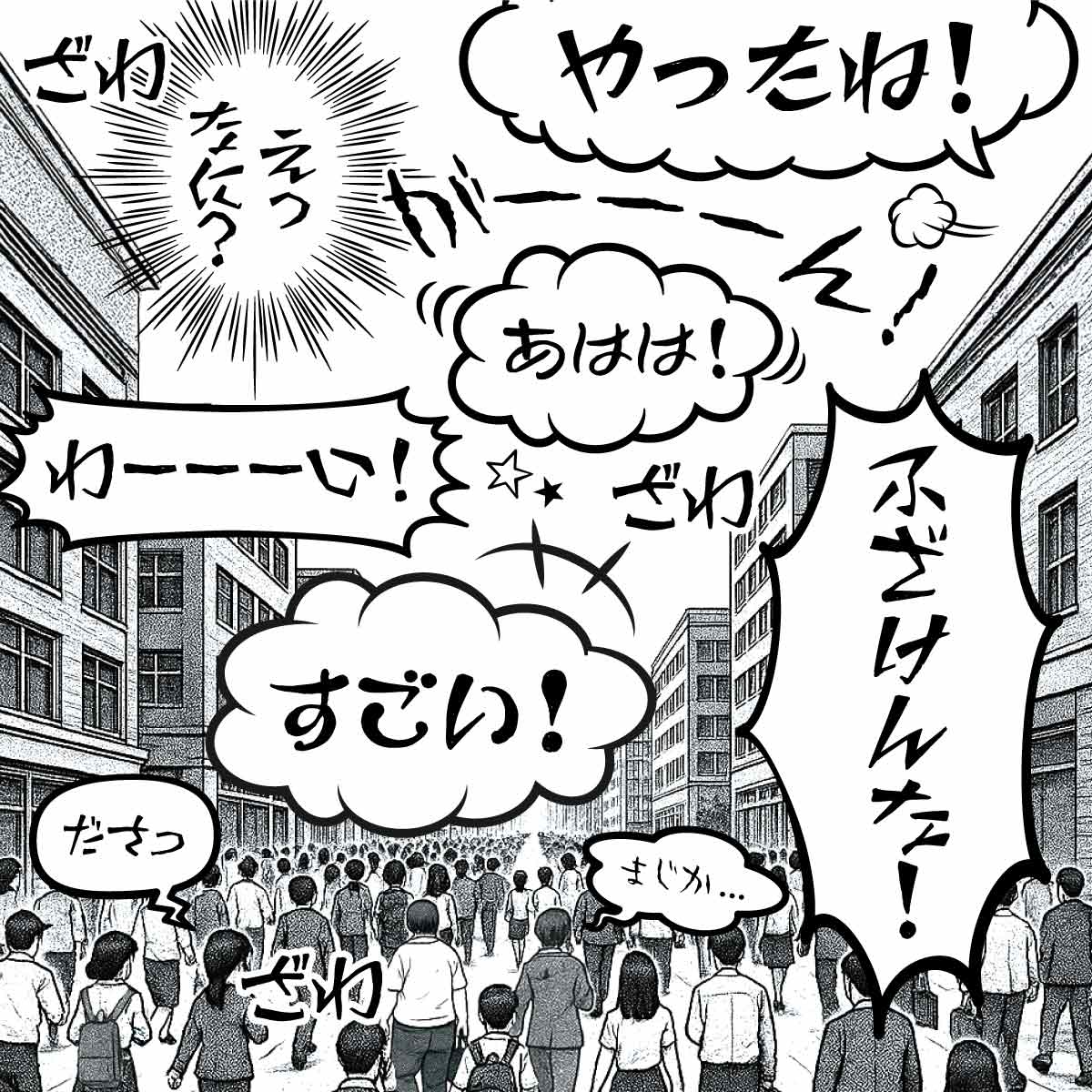
組み込みOK fontUcom ゲームで使える87書体セット
見本
セット1ゲームで使える87書体セット
レトロゲームのようなビットマップフォント6書体、タイトルやキャッチコピーに最適なデザインフォント10書体(AFSセリフゴシック、AF-ss、AFSテンドゥ)、本文などに最適な可読性の高いゴシック体14書体(AFSバーズアイ、AFSまるご風10書体)の日本語フォント30書体に加えて、感情表現に最適な仮名フォント12書体、ゲームのタイトルなどに最適な欧文フォント45書体の合計87書体を収録したセット商品です。さらに本セット商品をご購入いただいた方にはゲームやアプリケーションへの組み込み可能なライセンスもお付けいたします。
電光掲示板みたいなフォント AFS明朝16■R、電光掲示板みたいなフォント AFS明朝16●R、電光掲示板みたいなフォント AFSゴシック16■R、電光掲示板みたいなフォント AFSゴシック16●R、レトロゲームっぽいフォント AFSゴシック10■R、レトロゲームっぽいフォント AFSゴシック10●R、AFSセリフゴシック 2書体セット、AF-ss 4書体セット、AFSテンドゥ 4書体セット、AFSバーズアイ 4書体セット、AFSまるご風10書体セット、AFS感情(平仮名)フォント12書体セット、AFS復刻欧文フォント 24書体セット、SFっぽいフォント 10書体セット、AFS機械っぽい欧文フォント、AFSDisplay (表示器風フォントシリーズ2書体パック)
使用例
AFSゴシック10■R・AFSゴシック16■R
AFS感情-つらい・こわい・かなしい
AFS感情-やった・おこる・わらい・こわい・うるさい・すごい・かなしい・ださい・つらい
87書体セット収録内容
収録内容 1. 電光掲示板みたいなフォント AFS明朝16■R
電光掲示板みたいなフォント AFS明朝16■R 文字見本 電光掲示板みたいなフォント AFS明朝16■R 組み見本
電光掲示板みたいなフォント AFS明朝16■R
電光掲示板の雰囲気をアウトラインフォントで表現したフォント。街中で見られる電光掲示板のビットマップフォントをドットの形を■で表現した電光掲示板っぽい明朝フォントです。電光掲示板の雰囲気がでる外字,絵文字も100文字追加されております。
収録内容 2. 電光掲示板みたいなフォント AFS明朝16●R
電光掲示板みたいなフォント AFS明朝16●R 文字見本 電光掲示板みたいなフォント AFS明朝16●R 組み見本
電光掲示板みたいなフォント AFS明朝16●R
電光掲示板の雰囲気をアウトラインフォントで表現したフォント。街中で見られる電光掲示板のビットマップフォントをドットの形を●で表現した電光掲示板っぽい明朝フォントです。電光掲示板の雰囲気がでる外字,絵文字も100文字追加されております。
収録内容 3. 電光掲示板みたいなフォント AFSゴシック16■R
電光掲示板みたいなフォント AFSゴシック16■R 文字見本 電光掲示板みたいなフォント AFSゴシック16■R 組み見本
電光掲示板みたいなフォント AFSゴシック16■R
電光掲示板の雰囲気をアウトラインフォントで表現したフォント。街中で見られる電光掲示板のビットマップフォントをドットの形を■で表現した電光掲示板っぽいゴシックフォントです。電光掲示板の雰囲気がでる外字,絵文字も100文字追加されております。
収録内容 4. 電光掲示板みたいなフォント AFSゴシック16●R
電光掲示板みたいなフォント AFSゴシック16●R 文字見本 電光掲示板みたいなフォント AFSゴシック16●R 組み見本
電光掲示板みたいなフォント AFSゴシック16●R
電光掲示板の雰囲気をアウトラインフォントで表現したフォント。街中で見られる電光掲示板のビットマップフォントをドットの形を●で表現した電光掲示板っぽいゴシックフォントです。電光掲示板の雰囲気がでる外字,絵文字も100文字追加されております。
収録内容 5. レトロゲームっぽいフォント AFSゴシック10■R
レトロゲームっぽいフォント AFSゴシック10■R 文字見本 レトロゲームっぽいフォント AFSゴシック10■R 組み見本
レトロゲームっぽいフォント AFSゴシック10■R
レトロのゲームの雰囲気を醸し出すアウトラインフォント。昔ゲームで使用されていたビットマップフォントをドットの形を■で表現したレトロゲームっぽいフォントです。外字と絵文字を100文字追加!!
収録内容 6. レトロゲームっぽいフォント AFSゴシック10●R
レトロゲームっぽいフォント AFSゴシック10●R 文字見本 レトロゲームっぽいフォント AFSゴシック10●R 組み見本
レトロゲームっぽいフォント AFSゴシック10●R
レトロのゲームの雰囲気を醸し出すアウトラインフォント。昔ゲームで使用されていたビットマップフォントをドットの形を●で表現したレトロゲームっぽいフォントです。外字と絵文字を100文字追加!!
収録内容 7.AFSセリフゴシック 2書体セット
AFSセリフゴシック 2書体セット 文字見本 AFSセリフゴシック 2書体セット 組み見本
本セットではJIS90字形とJIS2004字形の2書体を同梱しています
AFSセリフゴシック 2書体セット JIS90字形とJIS2004字形の比較
AFSセリフゴシック 2書体セット
欧文のエジプシャン書体に近いデザイン。どっしりと足のセリフは腰の据わった安定したデザインで落ち着きや安定感を与えます。キャプションなど短い解説やロゴなどに応用ください。
収録内容 8. AF-ss 4書体セット